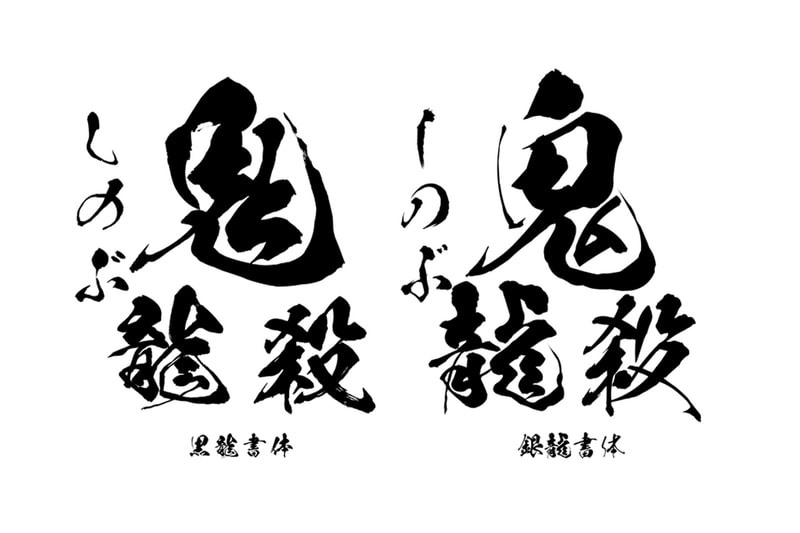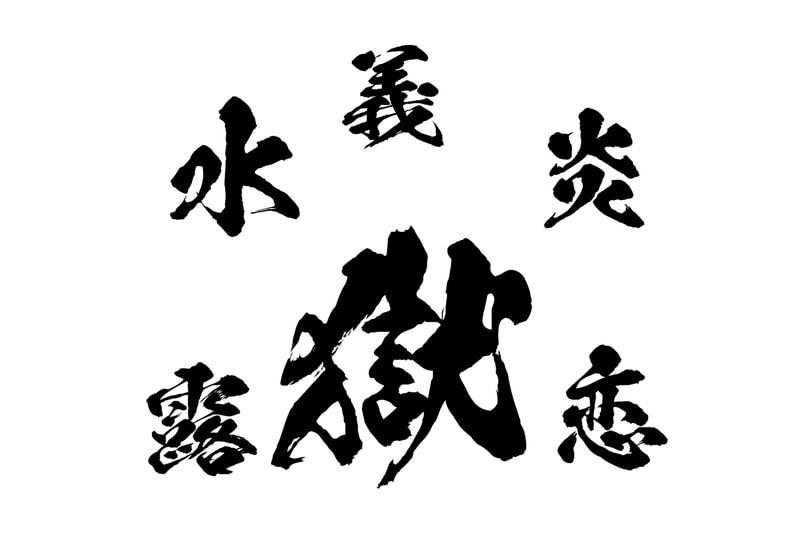
推出「鬪龍」、「陽炎」和「黑龍」等字體。
相信若對《鬼滅の刃》有所了解,除了精細作畫的華麗戰鬥畫面之外,時常出現在其中的書法毛筆字型也著時吸睛。在《鬼滅の刃》的動畫中,製作群使用了變體的日本昭和書体毛筆字型來呈現角色的名字,該字體由 84 歲書法家坂口綱紀所書寫而出,完美呈現出《鬼滅の刃》1912 至 1926的大正時代的時代感。